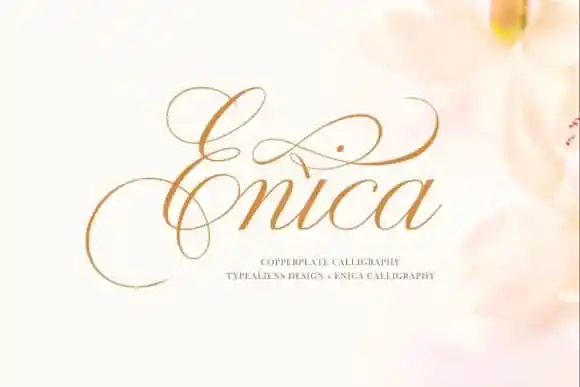
Olá a todos… Introduzimos aqui para vocês a Enica Calligraphy Font, uma linda fonte script criada à mão, com um estilo que remete ao desenho manual, resultando num belo e elegante resultado. Com sua influência de calligrafia classificada enquanto mantém um aspecto contemporâneo e fresco, a Enica é perfeita para quem busca uma fonte que transmite conforto e sofisticação. Esta exquisiteira fonte escrita à mão foi meticulosamente projetada para torná-la verdadeiramente única e querida pelos criadores de tipoaliens. Perfumando seu projeto com sua beleza natural, a Enica é ideal para aquela necessidade especial de adicionar um toque elegante que destacará seu trabalho. Desfrutarei muito da harmonia única que essa fonte traz às suas criações e ficarei encantado por ver como ela se adaptará ao seu estilo. Experimente a Enica e veja o impacto transformador que ela pode ter em seus projetos!